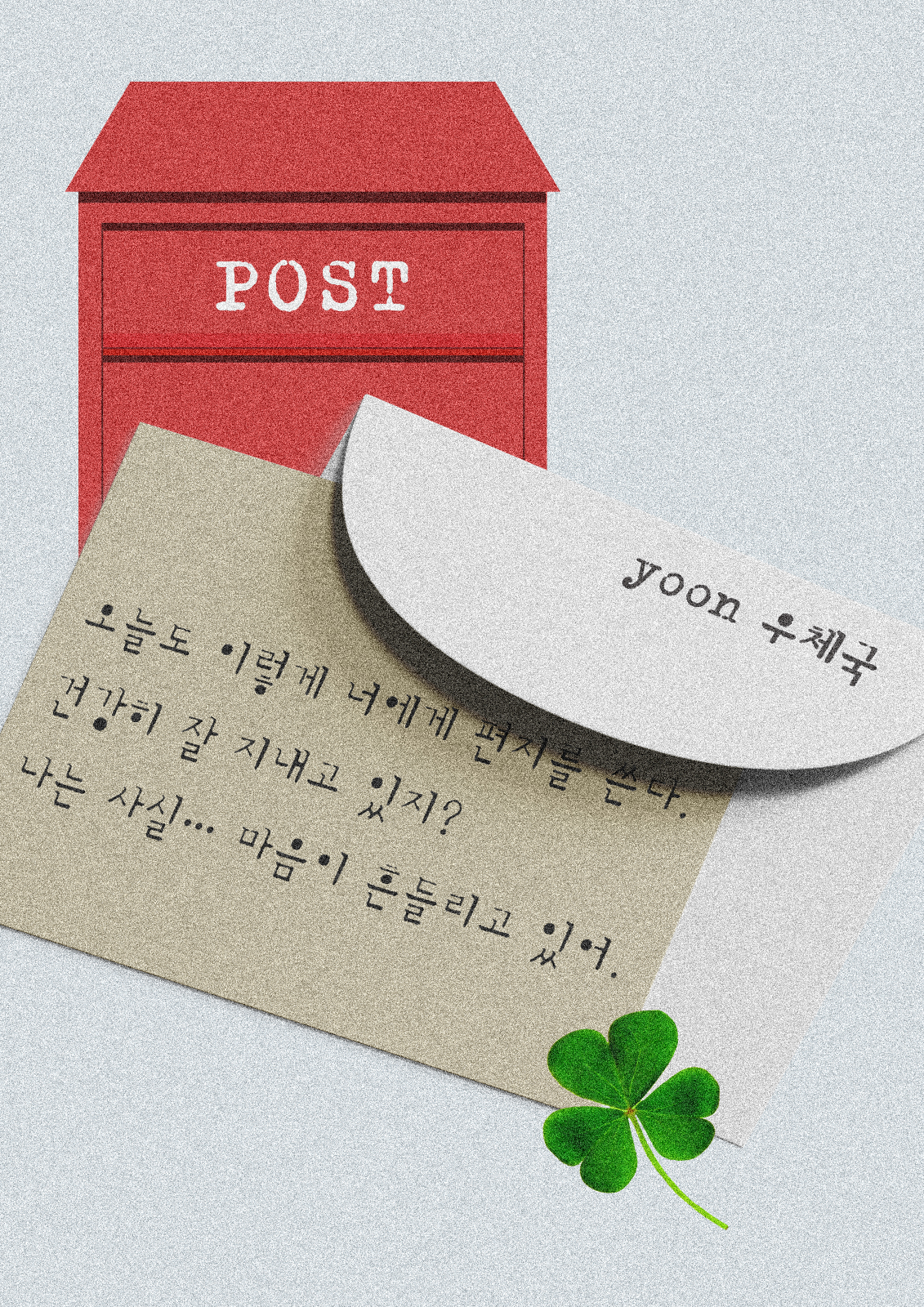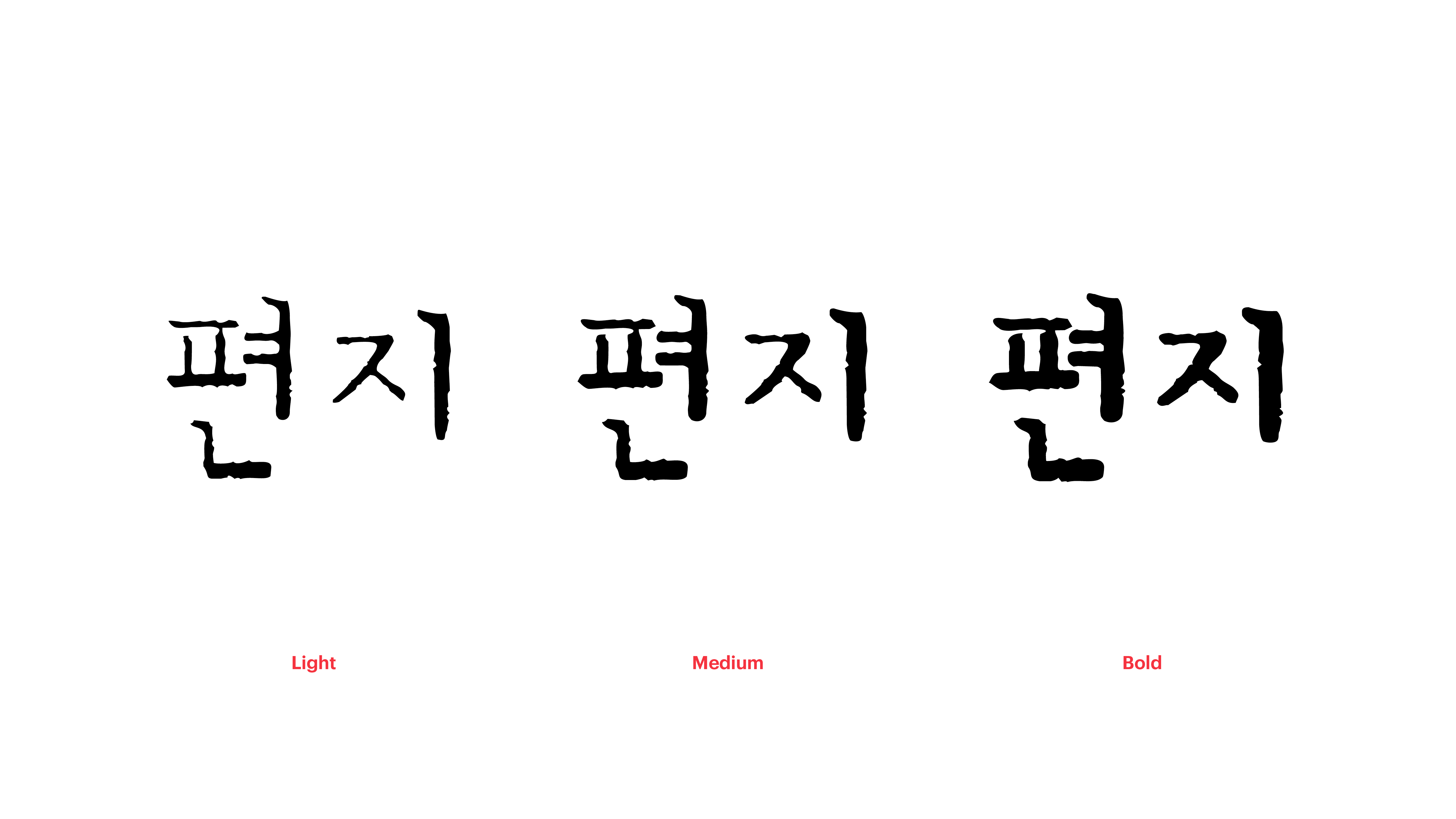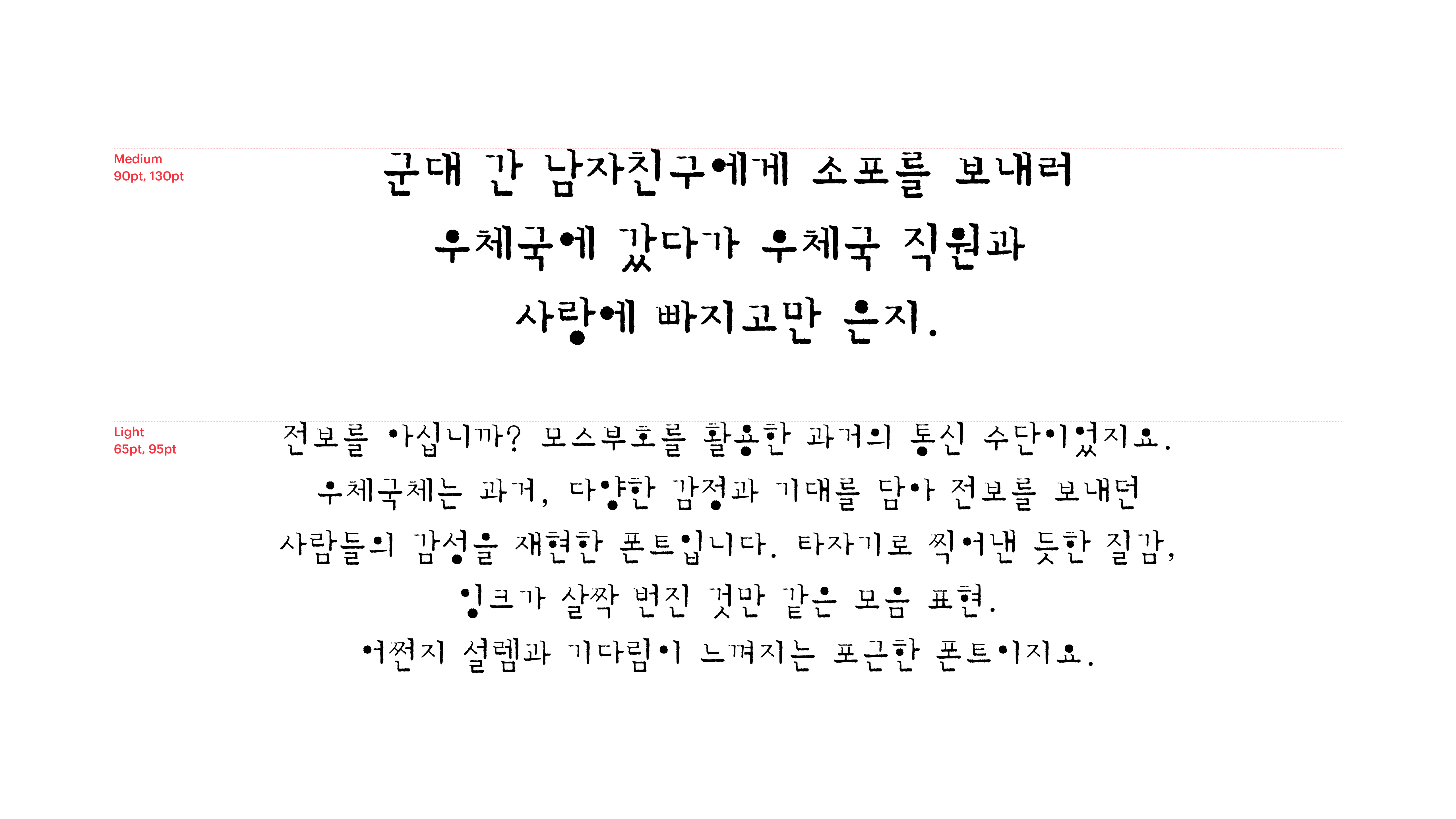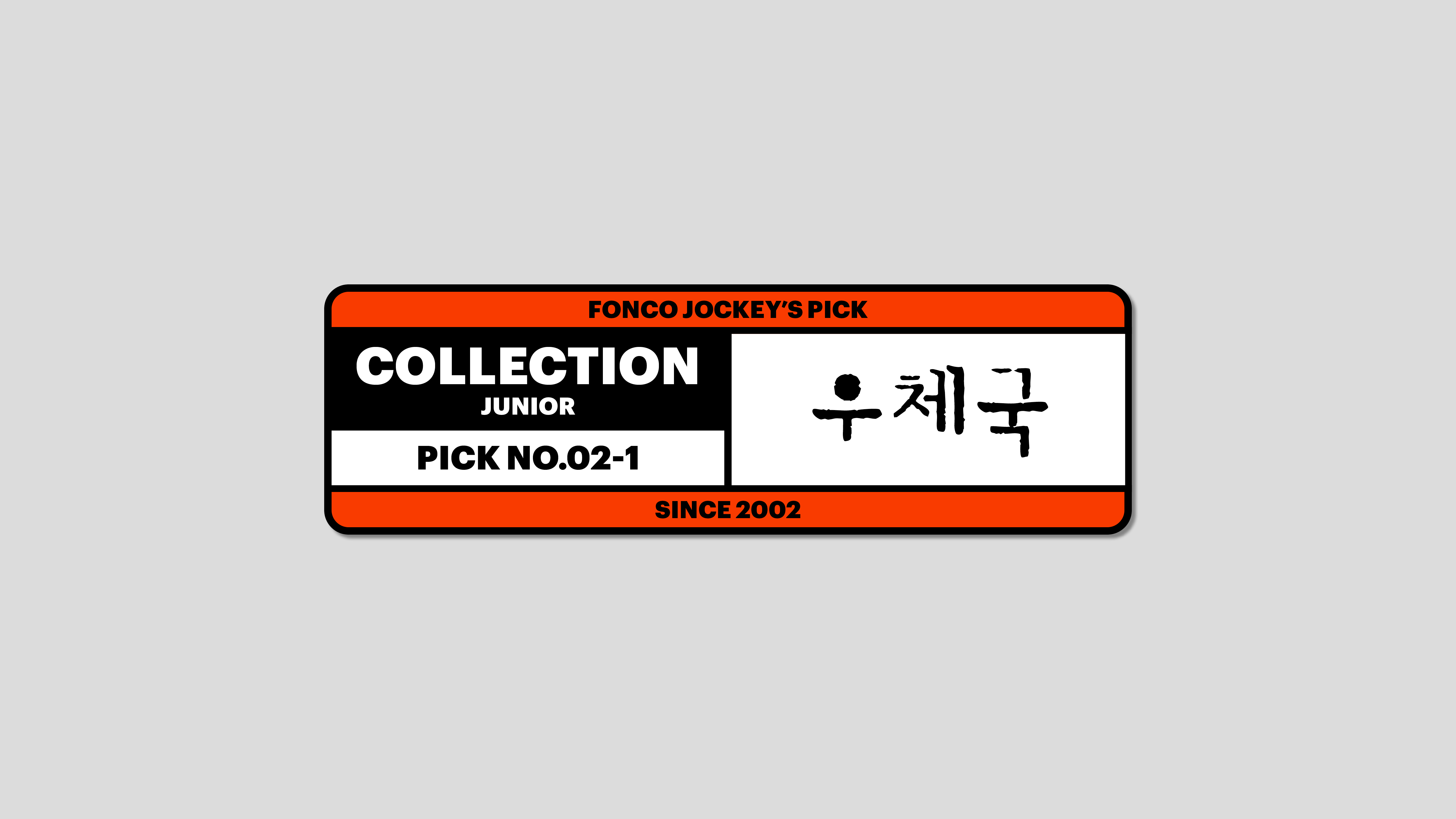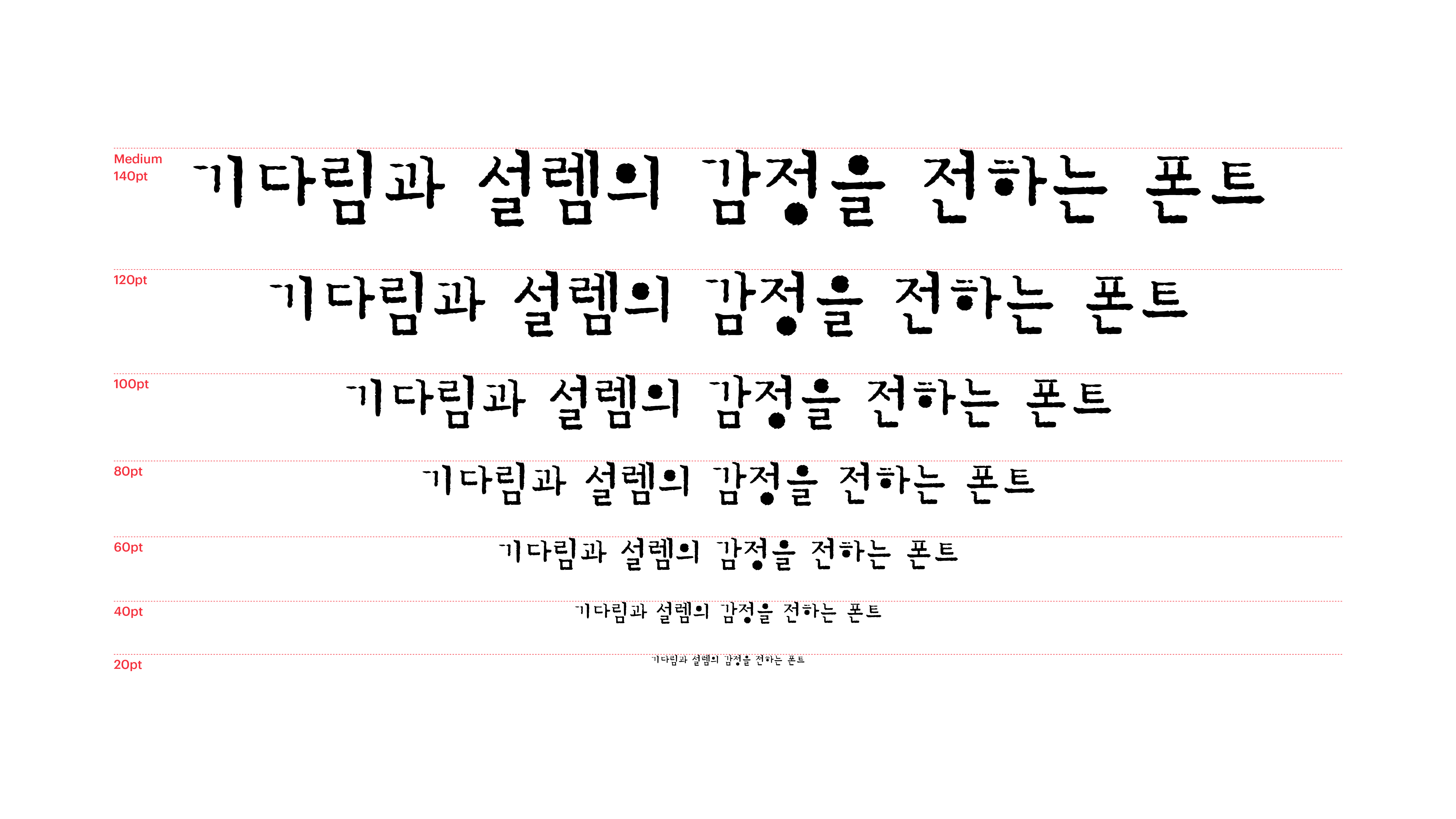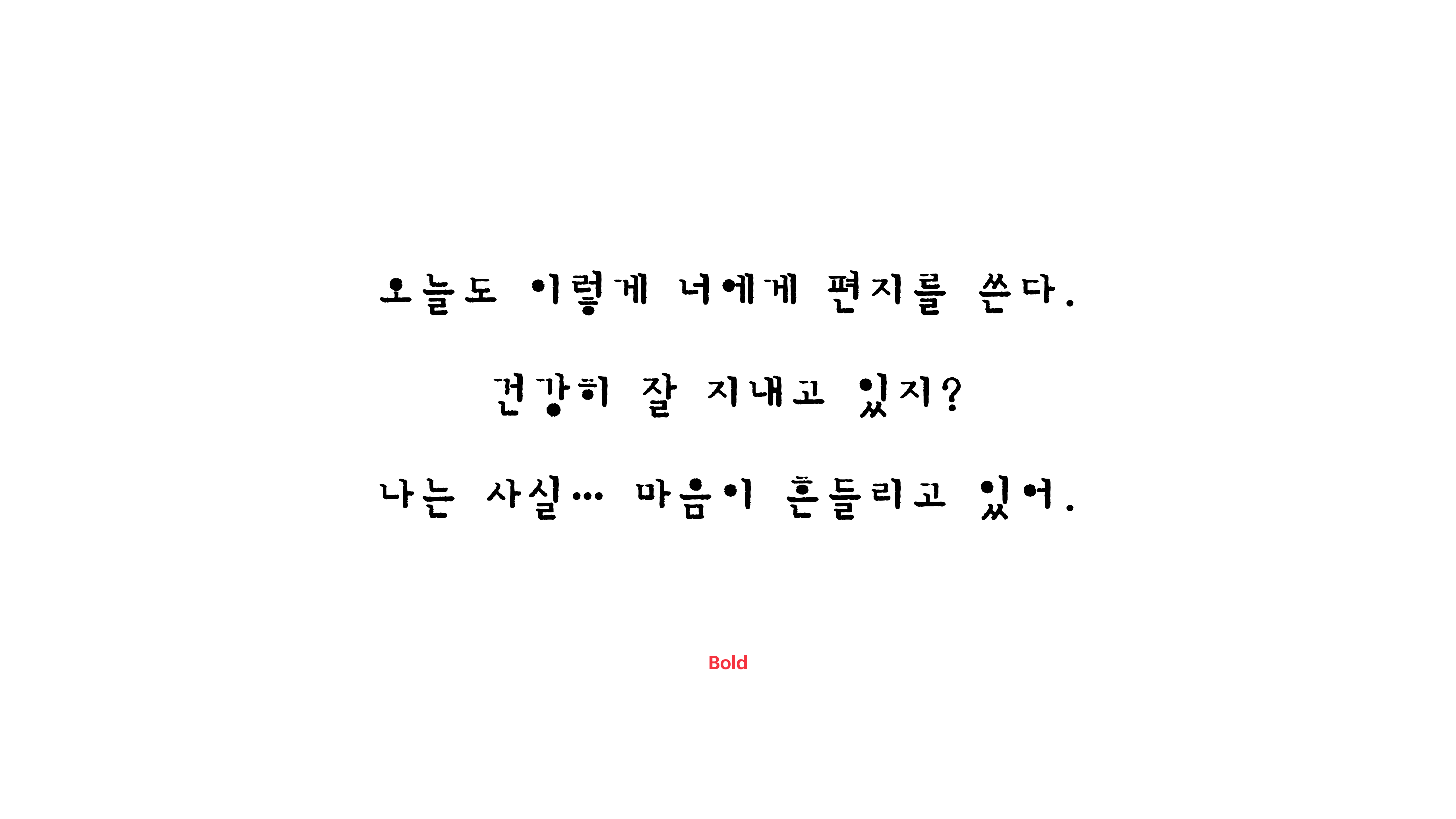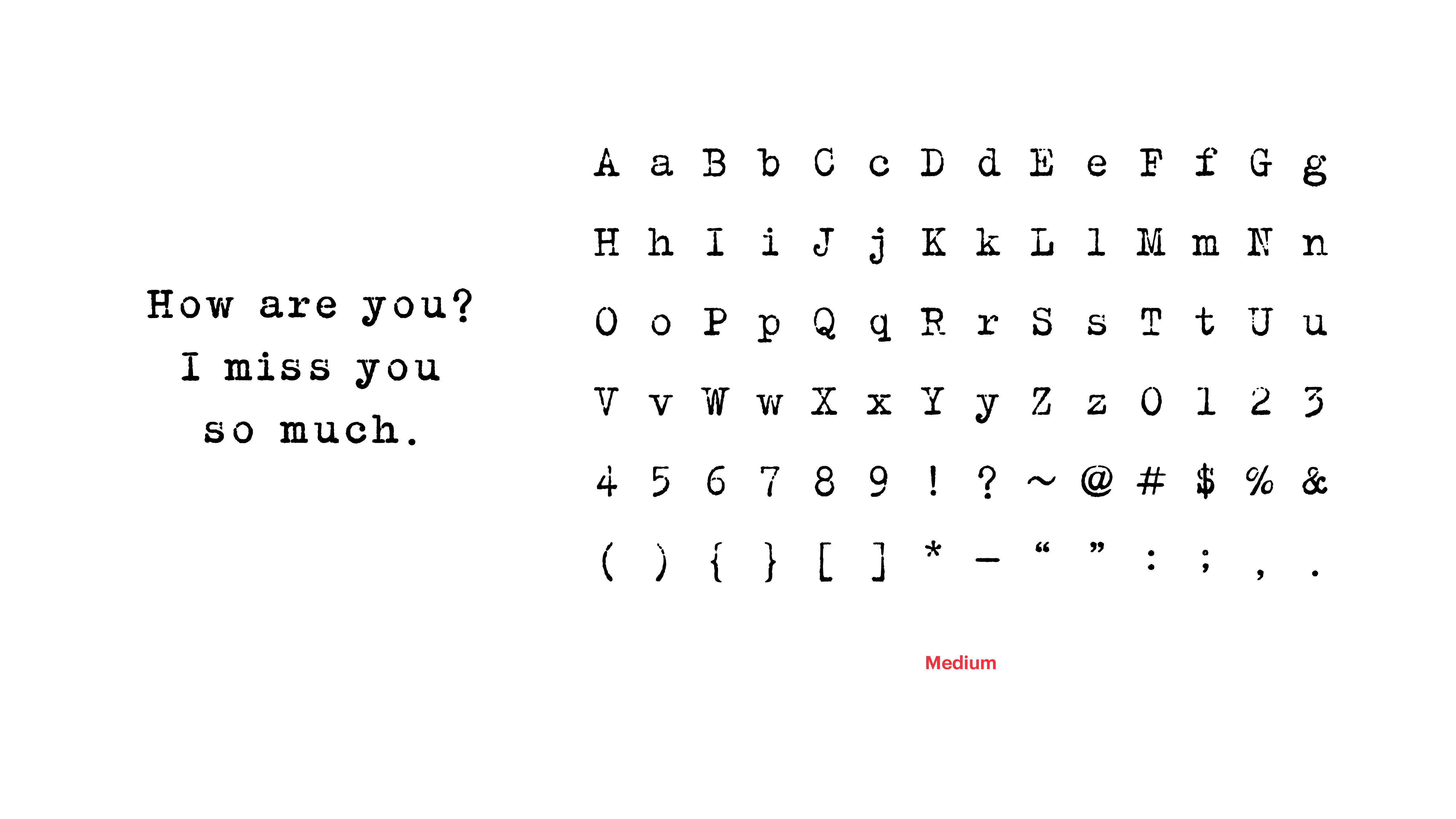
우체국
Yoon 우체국
전보를 아십니까? 모스부호를 활용한 과거의 통신 수단이었지요. 우체국체는 과거, 다양한 감정과 기대를 담아 전보를 보내던 사람들의 감성을 재현한 폰트입니다. 타자기로 찍어낸 듯한 질감, 잉크에 의해 번진 것만 같은 모음 표현. 어쩐지 설렘과 기다림이 느껴지는 포근한 폰트이지요.